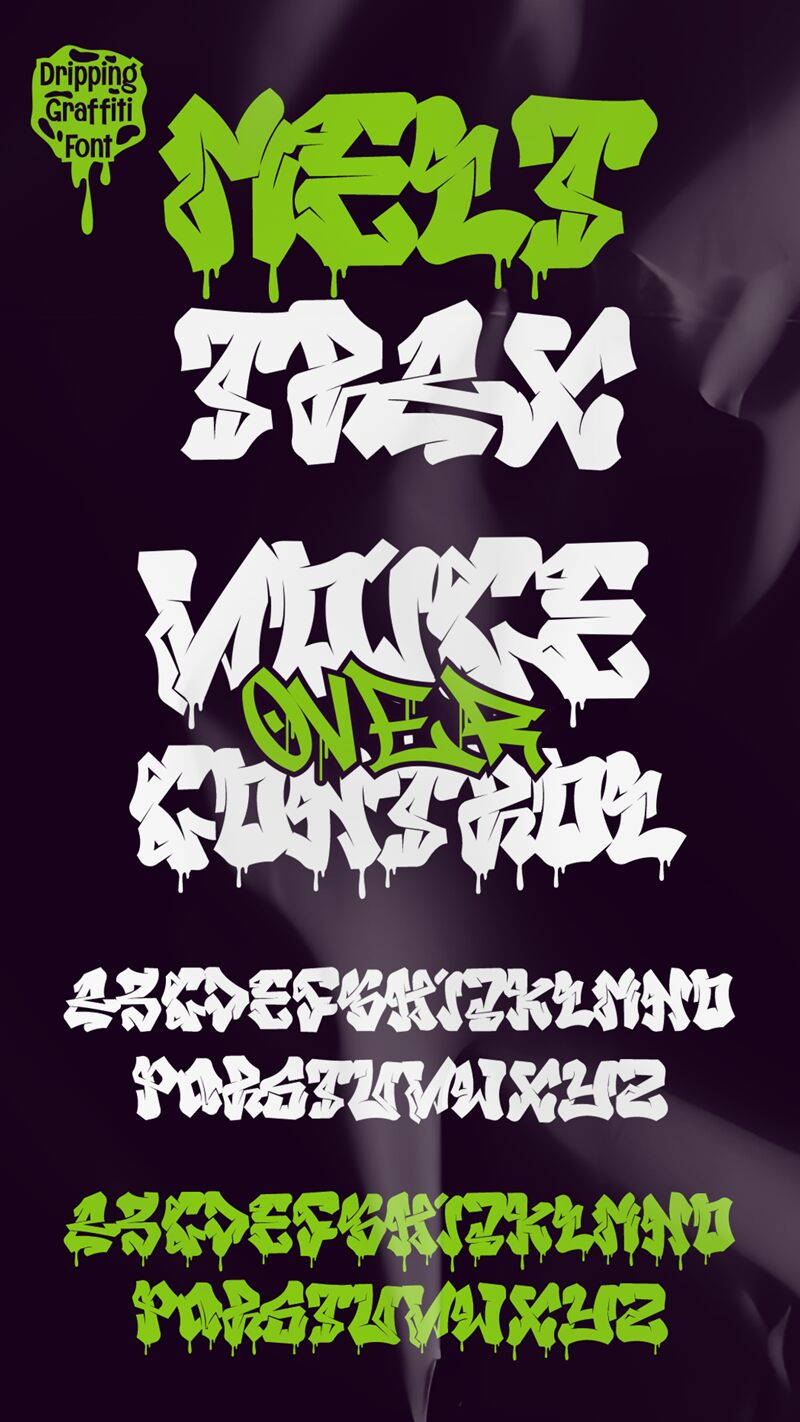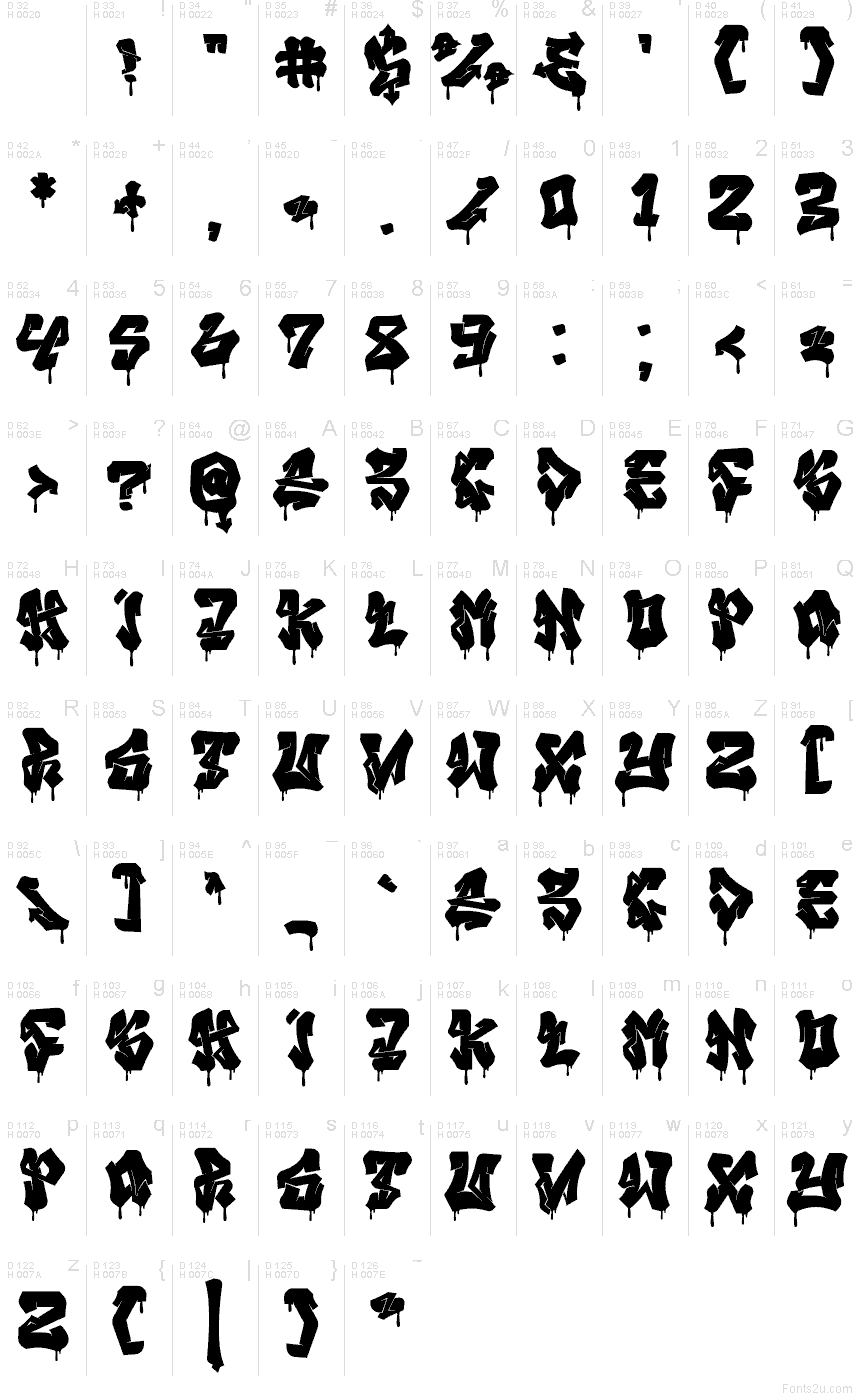
Melttrax Drip od Muhammada Panji Ramdhaniho a Ferbiyi TSA (Sipanji x Cikareotype) je bezplatné graffiti písmo s neotřelým, „inkoustovým“ charakterem, který vypadá, jako by barva ještě nestihla zaschnout. Písmena jsou zároveň ostrá a masivní – mají bodavé špičky, těsné spoje a sirupovité kapky, které visí pod linkou jako čerstvá barva na zdi. Je to výrazný font, který nepotřebuje žádné efekty navíc; i jediné slovo dokáže samo o sobě unést celou kompozici.
Melttrax Drip zazáří na obalech alb, skate a streetwearové grafice, titulech plakátů, náhledech pro YouTube, sadách samolepek i plakátech na akce, kde záleží na postoji. Díky nerovnoměrnému rytmu a kompaktní šířce působí nápisy úderně i při sazbě do více řádků. Pro popisky jej kombinujte s jednoduchým bezpatkovým písmem a nechte Melttrax Drip vyniknout tak, že jej použijete ve velké velikosti na čistém, klidném pozadí.